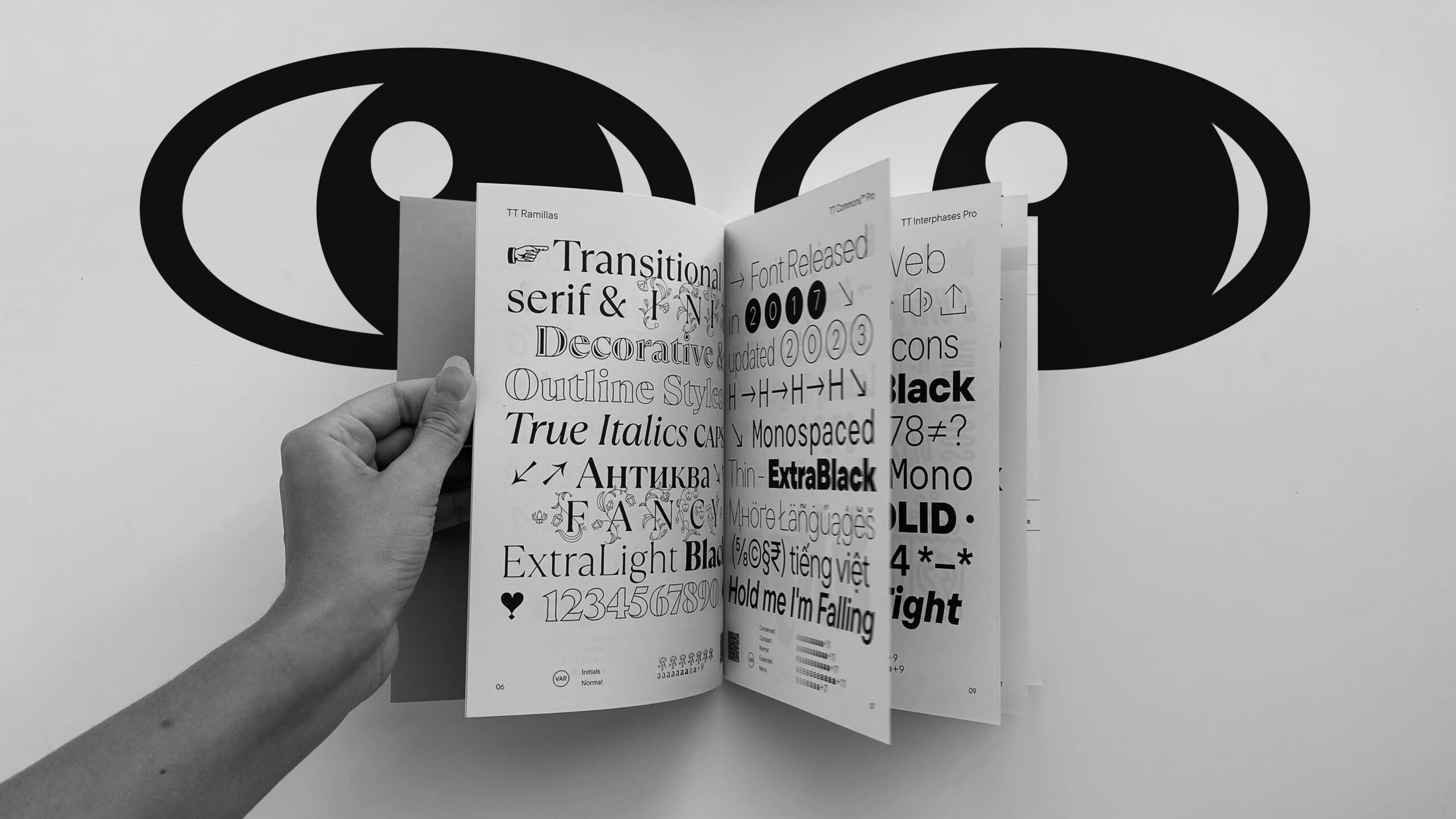
Печатный каталог TypeType
Здесь вы можете заказать бесплатный печатный каталог шрифтов TypeType, в котором собраны 30 самых актуальных гарнитур студии. В коллекцию вошли разные по характеру и сфере применения шрифты — от нейтральных гротесков до элегантных антикв, от текстовых шрифтов до выразительных заголовочных гарнитур.
Шрифты TypeType поддерживают до 280 языков и обладают расширенным составом знаков, многие семейства содержат вариативные версии. Каждый шрифт тщательно проработан технически и хорошо читается даже в маленьком размере и с любого устройства. Стилистические сеты, лигатуры и другие OpenType фичи еще больше расширяют возможности работы с текстом.